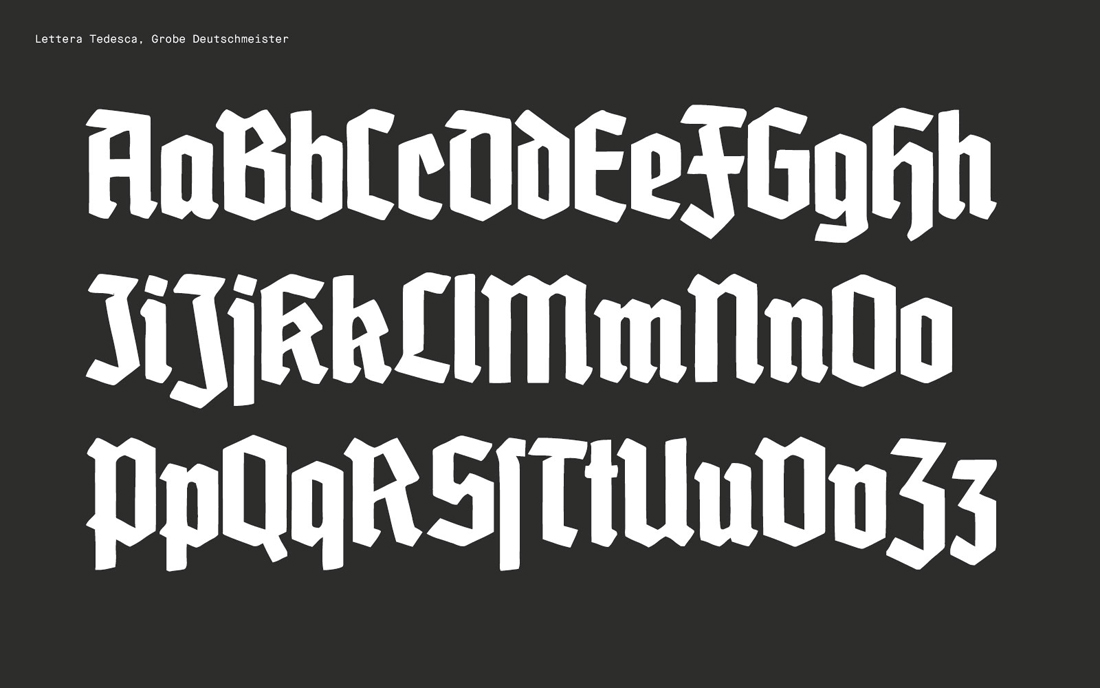
Алфавит и шрифты немецкого языка
Немецкий язык относится к германской группе языков с числом говорящих на нем 121 млн.человек в Германии, Австрии, Швейцарии, Лихтенштейне, Бельгии, Италии, Франции, Дании, Польше, Венгрии, Румынии, России, Украине, Люксембурге, Чешской республике, Словакии, Эстонии, Латвии, Литве, США, Канаде, Бразилии, Аргентине, Парагвае, Австралии, Южной Африке и Намибии.
Самые ранние памятники немецкой письменности относятся к 8-му веку н.э. и представляют собою фрагменты эпической поэмы, Песнь о Хильдебранде — магическая привлекательность и блеск немецкого языка, записанного в латинском манускрипте. Небольшой латинско-немецкий словарь, Аброганы, датированный 760г.
Появление немецкой литературы относится к 12-му и 13-му векам. Это были стихи, эпические поэмы и романы. Хорошо известный пример – эпическая поэма Nibelungenlied (Песня о Нибелунгах) и Тристан
Язык этих произведений сейчас известен как mittelhochdeutscheDichtersprache (Средневерхненемецкий язык). В этот период начинают появляться официальные документы на немецком языке и происходит постепенное вытеснение латинского языка.Виды немецкого письма
Верхненемецкий (Hochdeutsch)
Верхненемецкий язык начал приобретать статус литературного языка в 16-м веке. Начало этому процессу положил перевод Библии Мартином Лютером в 1534. Язык, который он использовал, частично основанный на разговорных формах немецкого, стал образцом письма.
Швейцарский немецкий (SchweizerdeutschorSchwyzerdutsch)
Разновидность немецкого языка, на котором говорит 4 млн.человек в Швейцарии, временами попадается в новеллах, газетах, личных письмах и дневниках.
Региональные диалекты немецкого, или Mundarten.
Также время от времени появляются в письменном виде: преимущественно в «народной» литературе и комиксах, как например, Астерикс.
Стили немецких рукописных шрифтов
Фрактура
Фрактура использовалась для печати и письма с 16-го века и до 1940г. Название «Фрактура» (нем.Fraktur) происходит от латинского словосочетания «ломаный шрифт«. Он назван так потому, что его декоративные извилистые начертания (завитушки) ломают непрерывную строчку слова. В немецком языке его обычно называют deutscheSchrift (немецкий шрифт).
Фрактура использовалась также и для других языков: финского, чешского, шведского, датского и норвежского.
немецкий алфавит
Примечание
Второй регистр строчных букв появляется в конце слога, кроме следующих сочетаний: ss, st, sp, sh и sch, тогда как первый пишется во всех остальных случаях. Символ ? ( scharfesS или Eszett) является сочетанием s и z, или сочетанием двух типов s.
Но о происхождении этого символа до сих пор спорят.
Пример текста, написанного шрифтом фрактура
немецкий текст с переводом
Шрифт Зюттерлина
Этот вид шрифта был создан берлинским рисовальщиком Л. Зюттерлином (1865-1917гг.), который смоделировал его на основе рукописного шрифта, которым пользовались в древнегерманской канцелярии. Этому шрифту обучали в немецких школах с 1915 по 1941 гг. Старое поколение до сих пор его использует.немецкий рукописный алфавит
Пример текста, написанного шрифтом Зюттерлин
Современный немецкий алфавит | ||||||||||||
A a | B b | C c | D d | E e | F f | G g | H h | I i | J j | K k | L l | M m |
a | be | ce | de | e | ef | ge | ha | i | jot | ka | el | em |
N n | O o | P p | Q q | R r | S s | T t | U u | V v | W w | X x | Y y | Z z |
en | o | pe | ku | er | es | te | u | vau | we | iks | upsilon | zet |
Пример текста
Alle Menschen sind frei und gleich an Wurde und Rechten geboren.
Прослушать запись текста
Перевод
Все люди рождаются свободными и равными в своем достоинстве и правах. Они наделены разумом и совестью и должны поступать в отношении друг друга в духе братства.
(Статья 1 Всеобщей декларации прав человека)
78 Печатный шрифт Мондиаль Фетт (Mondial Fett). Оформил немецкий художник
Ганс Бон (Hans Bohn)
79 Печатный шрифт Корвинус (Corvinus). Оформил швейцарский художник Имре
Р е й н е р (Imre Reiner)
80 Петровский шрифт, 1710 г. Один из первых вариантов шрифта (По Якову Чер¬
ни X о в у)
81 Елизаветинский шрифт, 1737—1753 гг. (По Якову Чернихову.)
82 Русская антиква. Рисована по мотивам шрифтов XVIII в.
83 Русская антиква. Рисовал московский художник Вадим Лазурский
84 Антиква. Рисовал американский художник И. Альберт К е в е н е г (J.
Albert
Cavanagh).
85 Русская антиква. Нарисована по мотивам представленной на противоположной
странице антиквы американского художника И. Альберта К ев ен era (J. Al¬
bert Cavanagh)
86 Антиква. Рисовал немецкий художник Альберт Капр (Albert Карг)
87 Египетский шрифт. Рисовал немецкий художник Альфред Финстерер (Alfred